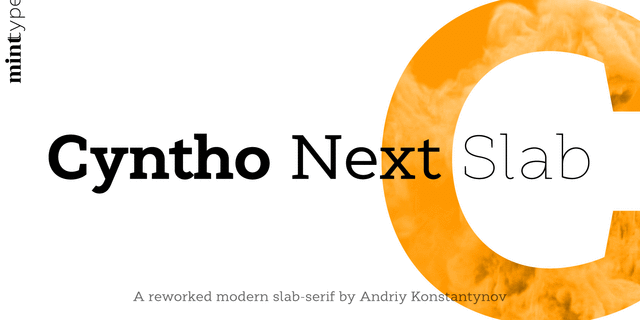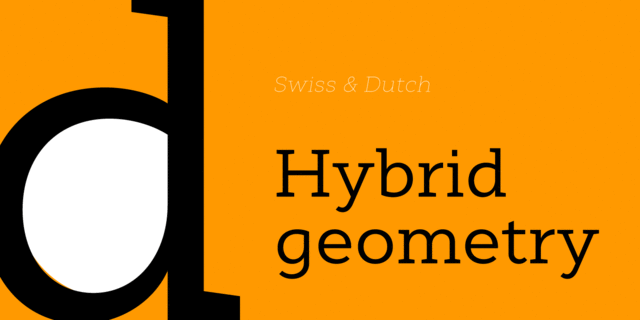
Cyntho Next Slab – брусковый компаньон шрифта Cyntho Next. Это современный геометрический брусковый шрифт, в основе которого гибридная каплевидная контрформа. Имеет широкий спектр языковой поддержки, включая кириллицу, богатые функции OpenType. Он идеально подходит для журналов, плакатов, рекламы, фирменного стиля и многого другого.
Шрифт разработал Андрей Константинов в 2019 году.